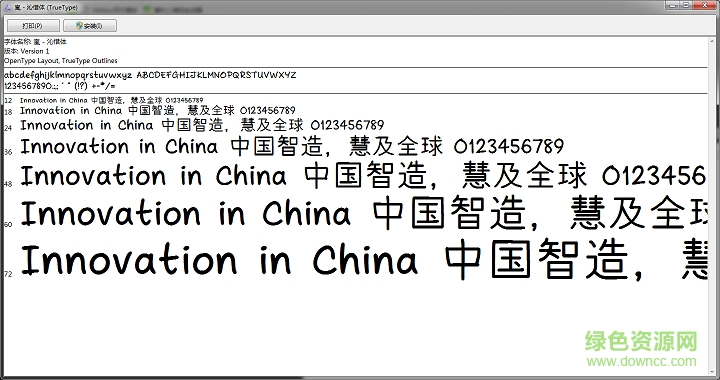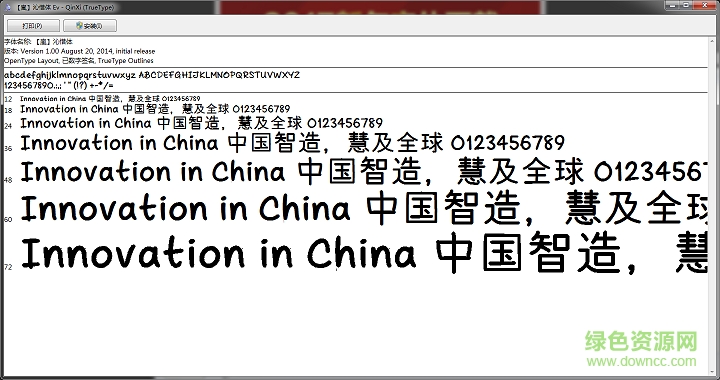
嵐沁惜體
沁惜體字體全稱嵐沁惜體,原本是一款手機(jī)字體,后移植成電腦字體。綠色資源網(wǎng)還帶來了沁惜體ttf加粗版,喜歡的朋友,趕快下載體驗(yàn)吧!
沁惜體介紹
沁惜體以圓體字體為原形,將一些筆畫進(jìn)行了變形修改,使字體在具有平滑的圓體風(fēng)格的同時,又兼具兒童卡通風(fēng)格,喜歡的朋友安裝一下吧。